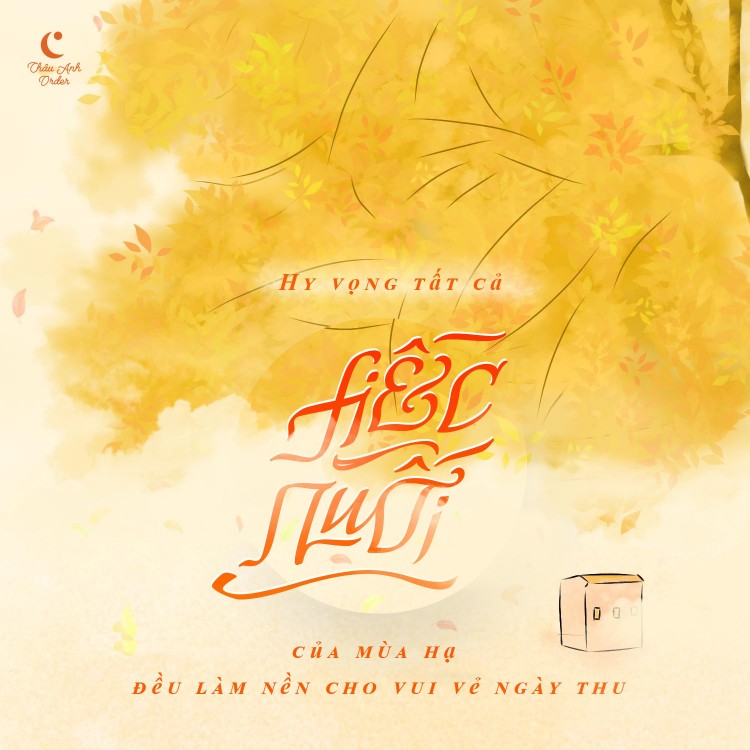
Font việt hóa MTD Capellina Script
Tải Font việt hóa MTD Capellina Script Miễn Phí Cho Thiết Kế Bay Bổng
Giới thiệu về Font việt hóa MTD Capellina Script
Trong thế giới đồ họa hiện đại, việc tìm kiếm một bộ Font Miễn Phí chất lượng luôn là ưu tiên hàng đầu của các bạn học sinh và giáo viên. Font việt hóa MTD Capellina Script là một trong những lựa chọn tuyệt vời nhất dành cho những ai yêu thích phong cách viết tay uyển chuyển. Đây là một phông chữ dạng Script với những đường nét thanh mảnh, bay bổng nhưng vẫn giữ được sự rõ ràng cần thiết. Việc sử dụng Font việt hóa MTD Capellina Script giúp các bài thuyết trình, thiệp chúc mừng hay báo tường trở nên sinh động và có hồn hơn rất nhiều. Với bộ mã Unicode đã được tối ưu hóa, bạn có thể dễ dàng gõ tiếng Việt có dấu mà không lo bị lỗi hiển thị.
Đặc điểm nổi bật của Font việt hóa MTD Capellina Script
Phong cách thiết kế nghệ thuật
Điểm mạnh nhất của Font việt hóa MTD Capellina Script chính là sự kết hợp hài hòa giữa nét thanh và nét đậm. Mỗi ký tự đều được chăm chút kỹ lưỡng để tạo ra cảm giác như được viết bằng bút mực thủ công. Điều này rất phù hợp cho các dự án thiết kế mang tính cá nhân hóa hoặc đòi hỏi sự tinh tế cao.
Tính ứng dụng linh hoạt trong học tập
Không chỉ dùng trong thiết kế chuyên nghiệp, phông chữ này còn cực kỳ hữu ích trong môi trường học đường. Các em học sinh có thể dùng để trang trí bìa tiểu luận, trong khi giáo viên có thể ứng dụng vào việc thiết kế bài giảng điện tử để thu hút sự chú ý của học sinh. Sự mềm mại của nó giúp giảm bớt vẻ khô khan của các văn bản thông thường.